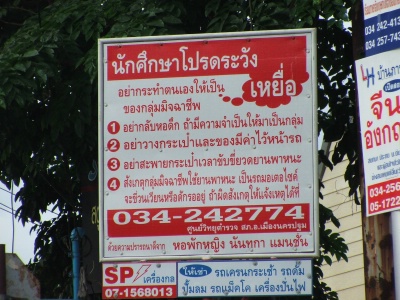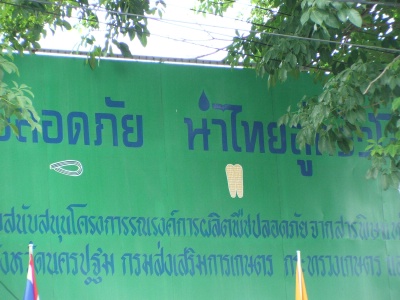
ฟอนต์ไม่เหมาะ
มันหลบไอ้นั่นไปนิดนึงครับ กลัวจะไปบาดเข้า
นั่นไม่ใช่รูปภาพครับ มันเป็นกระจก เห็นห้องที่อยู่ข้างหลังไหมครับ
บาดอะไรเหรอครับ :21:
บาดไอ้นั่นครับ
ไปงานรับปริญญาที่ศิลปากร ทับแก้วมาเมื่อวานซืน
พอดีหน้ามหาลัยรถติดมาก ตูเลยถ่ายป้ายข้างถนนแถวนั้นมาให้ดูกันเล่นๆ
อันแรก
ลองถามตัวเองดูว่า อ่านปราดเดียวแล้วเป็นคำว่าอะไรครับ :31:
อันที่สอง
ถามว่าอ่านว่า นำ หรือ น้ำ ครับ (อยากรู้ว่าตูคิดไปเองคนเดียวหรือเปล่า)
1. นักศึกษาโปรดระวัง อย่าทำตนเป็นของมิจฉาชีพ :34:
2. นำนะ แต่ให้ความรู้สึกเหมือนน้ำ
นักศึกษาโปรดระวังเหยื่อ  :39:
อ่านว่า นำ  :39:
นักศึกษาโปรดระวังเหยื่อ
อย่ากระทำตนเองให้เป็น
ของกลุ่มมิจฉาชีพ
เจออันนี้มาจากในทีวี เลยจับภาพมาฝากกัน
ดูในจอคอมมันก็ชัดเจนดีอยู่หรอก แต่พอดูในทีวี มันเป็นคำว่า "ข่าวถึก" แฮะ :31:
คือเรื่องการใช้ไทโปกราฟีไม่เหมาะสม
ส่วนมากผมมักจะมองและค่อนข้างขัดใจกับ Lettering ของชืื่อภาพยนต์ภาษาไทย (และที่แปลเป็นไทย) มากกว่าครับ
ยกตัวอย่างง่ายๆล่าสุดเลย หนังเรื่องอะไรนะ มี่ๆ  :49:
ก็ใช้ฟอนต์ Kodchiang พิมพ์ลงไปดื้อๆ ซะอย่างนั้นเลย ทั้งๆที่ผมรู้สึกว่า
mood and tone ของหนังมันต้องไม่ใช่ฟอนต์นี้แน่ๆ
หรือแม้กระทั่งหนังไทยบางเรื่อง ก็ใช้ฟอนต์แบบโมเดิร์นพิมพ์ลงไป ใส่เอฟเฟกต์นิดๆหน่อยๆ
ทั้งๆที่หนังก็เป็นหนังสยองขวัญ  :01:
ที่เขาทำดีๆ ก็มีอยู่หลายเรื่องนะโม่ :31:
บางเรื่องยังนึกอยากได้เลย (หลายเรื่องทำเป็นฟอนต์เลยด้วยซ้ำ)
แต่หลายเรื่องก็เผาจริงๆ :08:
บางเรื่องเข้าใจครับว่าสวยจริงๆ ( พูดง่ายๆคือมันดูผ่านการออกแบบมา )
แต่บางเรื่องเหมือนเอากิตติธาดามาแปะลงไปเลย เติมเอฟเฟกต์นิดๆหน่อยๆพอเป็นพิธี  :01:
ถ้าเปลี่ยน เพื่อ เป็น พลัง นะ  :39: